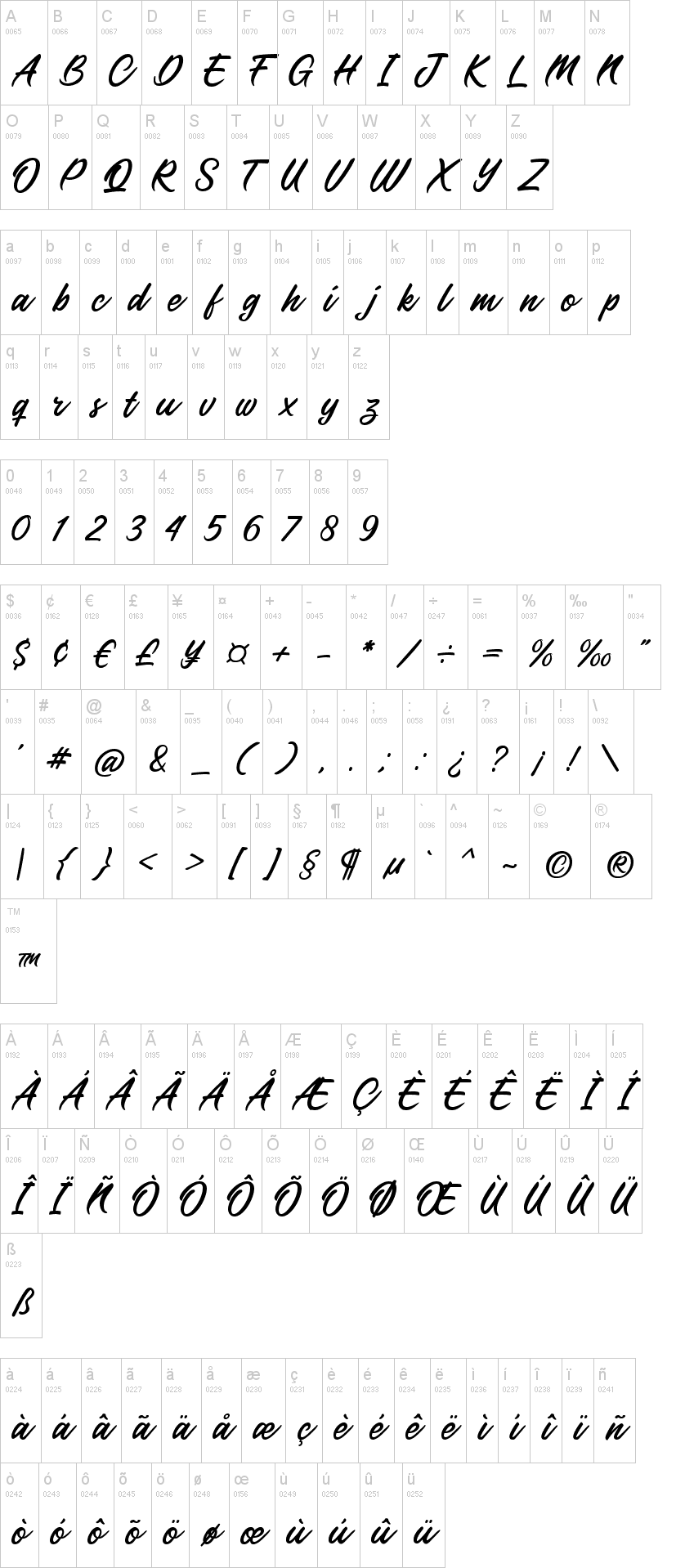
Galloped 字体是一款由英国设计师 Tom Chalky 创作的一款手写字体,它采用粗犷、鲜明的线条,可以带给你更多的灵活性和自由性,而且可以让你的设计更加有趣。它的笔触非常细腻,可以让你的文字变得更加有表现力,而且它的字体设计也非常的漂亮,可以让你的设计更加精致。内容介绍
Galloped是一款非常不错的手写艺术字体,具有很好的视觉感,适合于文化类的宣传设计、商业类品牌的广告和产品包装设计以及个性化文字排版等较多场景。